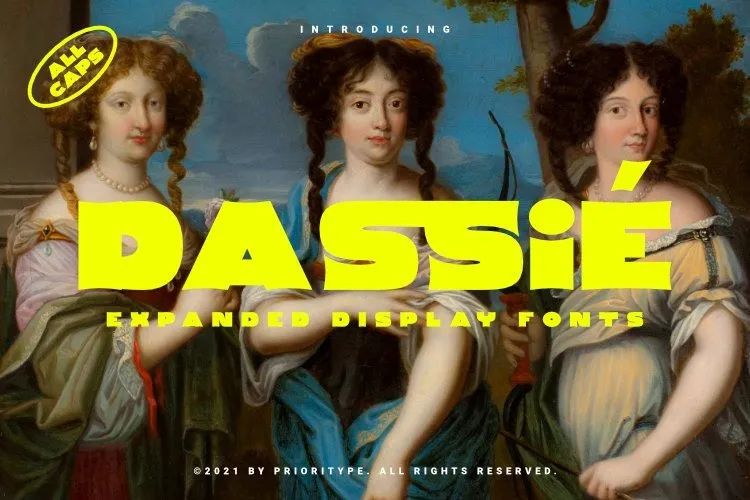
Dassie Display Font – Download Grátis
A fonte Dassie Display Font é uma escolha ideal para designers que buscam imprimir estilo em suas criações digitais. Inspirada na fauna do sul africano, essa serif font apresenta um toque único e encantador, adequado tanto para designs modernos quanto aqueles que remetem ao passado. Perfeita para os artistas digitais atuais, ela oferece uma paleta de opções únicas para a criação de designs variados como camisetas personalizadas, capas de livros, posters e até mesmo páginas de landing page ou materiais promocionais que ganham vida com seu visual vibrante. Com o Dassie Display Font, designers podem transformar ideias em realidade, entregando aos usuários um design atemporal e inovador. Se você busca uma fonte para dar vida a suas criações digitais, Dassie Display Font é uma escolha sólida.